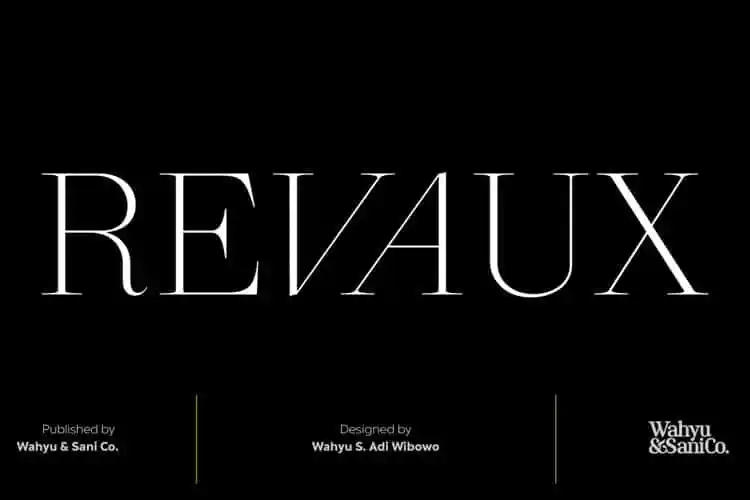
Revaux Serif Font
Revaux Serif é uma elegante tipografia serif que traz a sofisticação dos traços terminais em sua forma moderna. Lançada pela equipe de Wahyu e Sani, esta fonte oferece 304 gílios, incluindo alternativas e ligaturas, e apoia mais de 61 línguas latinas. Com seus detalhes meticulosamente criados, Revaux Serif é uma escolha perfeita para designers que buscam um equilíbrio entre elegância moderna e sofisticação tradicional. Seja em logotipos, materiais gráficos ou fontes legíveis em grandes tamanhos de tela, esta fonte oferece uma variedade incrível que certamente deixará seu trabalho ainda mais impecável.